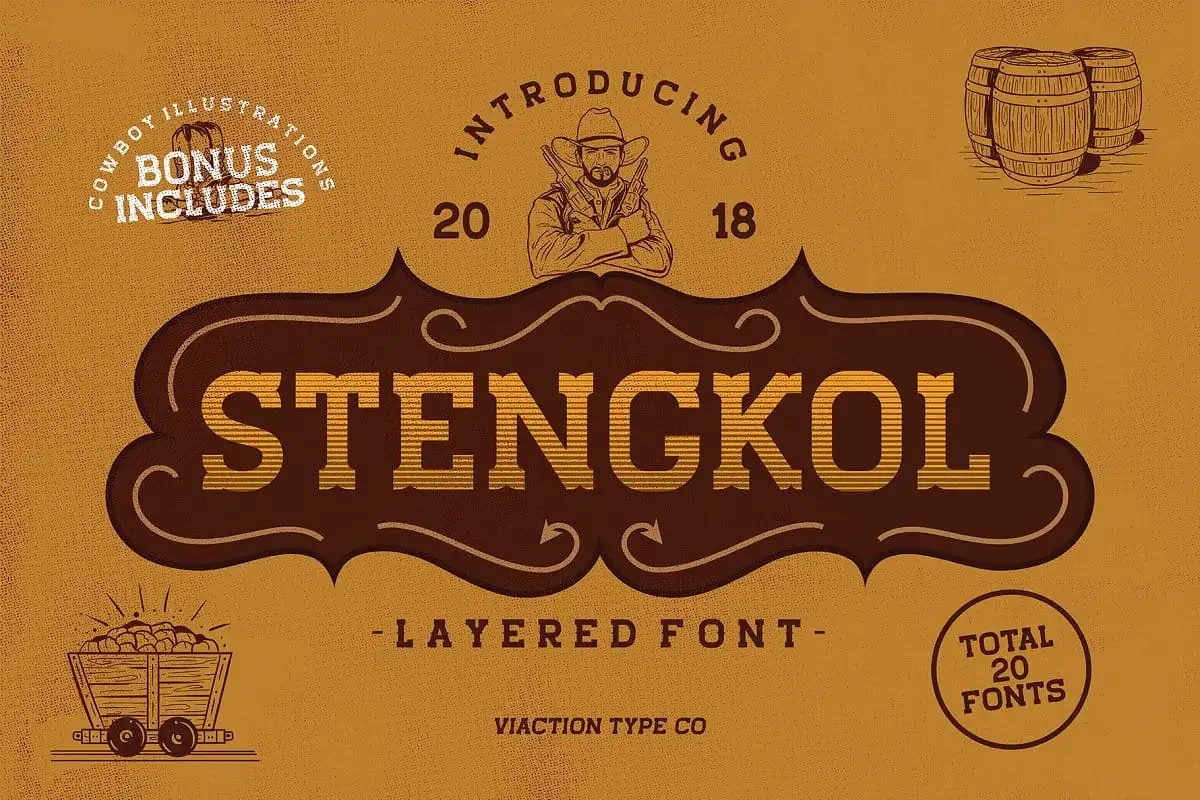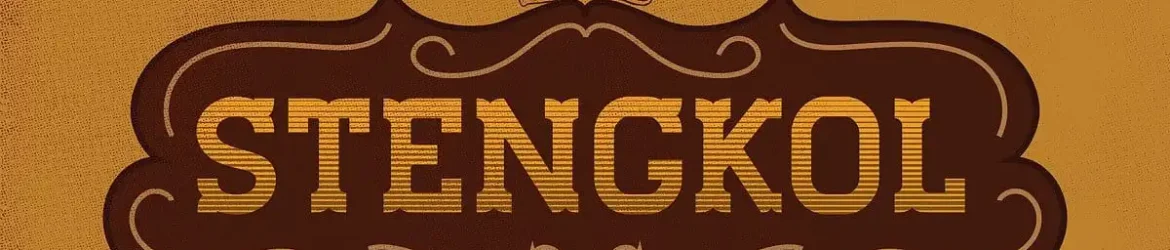
Esse é um novo conjunto de fontes familiares que inclui 20 tipos diferentes. Introduzimos Stengkol Typeface! Desenhado e compartilhado pela Viaction Type.Co., a família Stengkol compreende diversos estilos de fonte, combinadas em uma única família, proporcionando uma variedade impressionante para designers digitais. Esta famosa fonte é perfeitamente adaptada para diversos usos, desde t-shirts e merchandising até aplicações publicitárias como posters e sinais. O conjunto ainda inclui um desenho de índio cowboy que combina perfeitamente com a proposta do design. Stengkol Font Family é um recurso versátil para designers digitais, ideal tanto para personalizar produtos finais quanto para criar logotipos ou qualquer tipo de arte digital. Com mais de uma dúzia de estilos diferentes disponíveis na fonte, você pode escolher o que melhor se adequa ao seu design. Stengkol Font Family é perfeito para aqueles que procuram um conjunto completo e versátil de fontes com vários modos de usos possíveis no mesmo desenho. Se você está pronto para experimentar esta incrível oferta única, agora pode comprar todo o nosso grande leque de 20 tipos fonte em uma só compra. Que tal incluir este fantástico conjunto em seu próximo projeto?